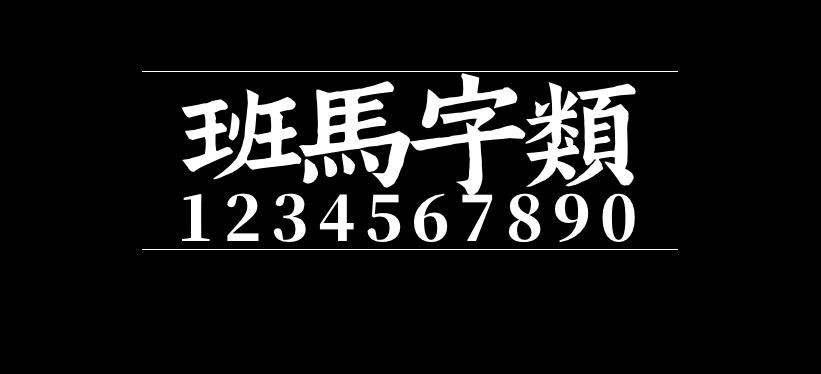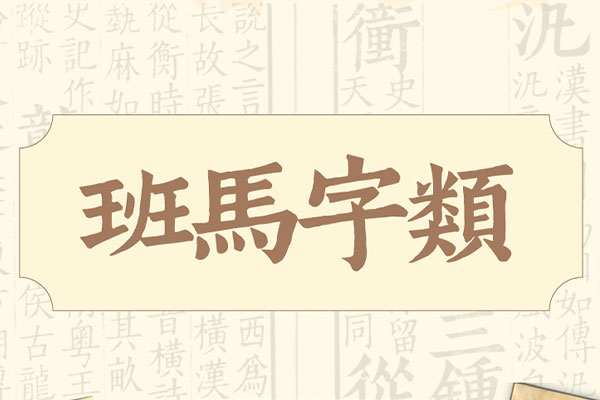
四声编排,考证训诂,辨别音声,并对假借通用诸字罗列详备。班马字类(创客贴班马字类)的作者是创客贴团队,在主创郑庆科的带领下历时数月,将这本古代字典中包含的汉字开发成了现代电脑字库,采用Unicode编码,收录汉字1800余个。
班马字类字库包含众多非常用汉字、异体字,亦是汉语言爱好者的便捷工具。需要注意班马字类字体并不是标准字库,收录的汉字有限,具体如下: